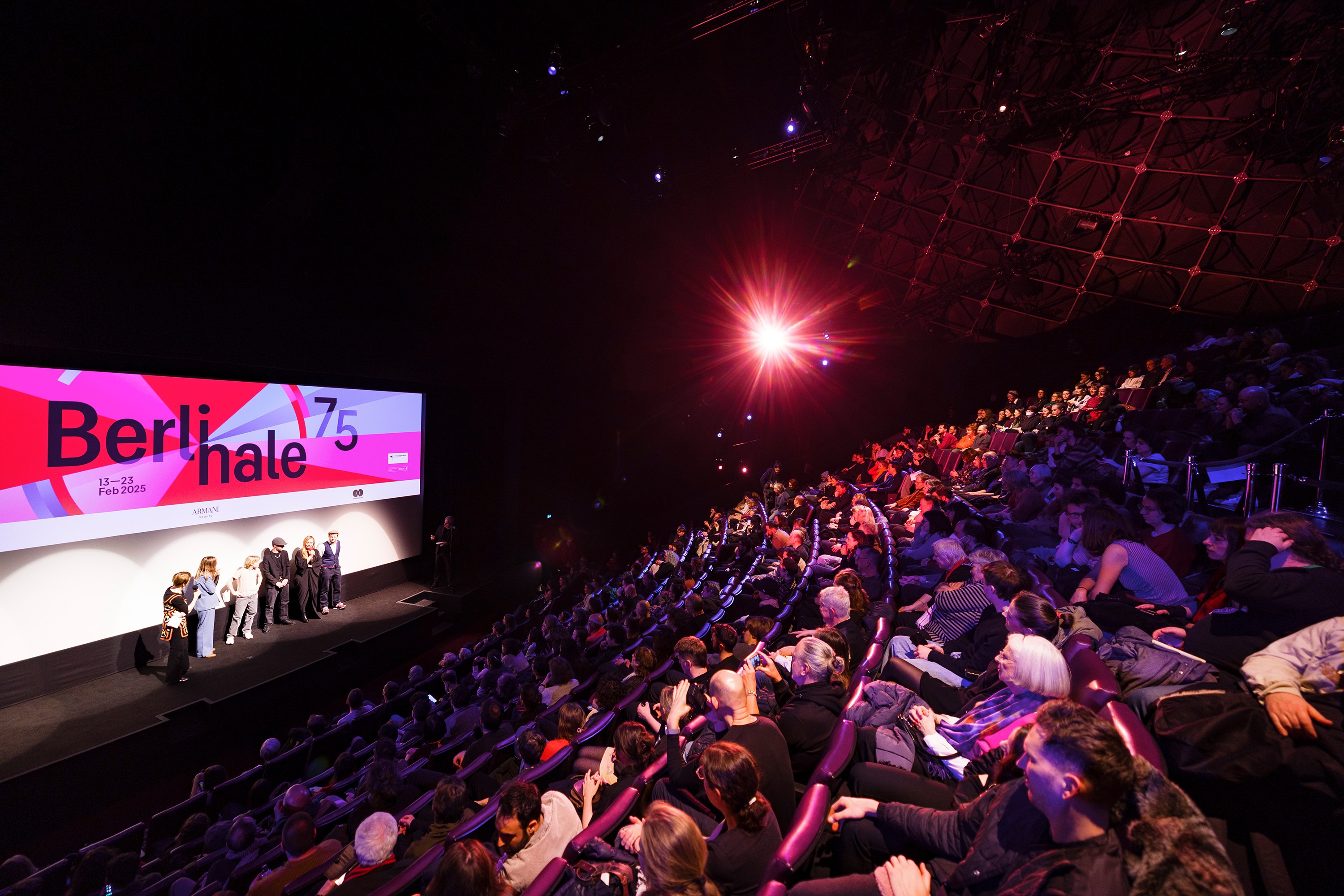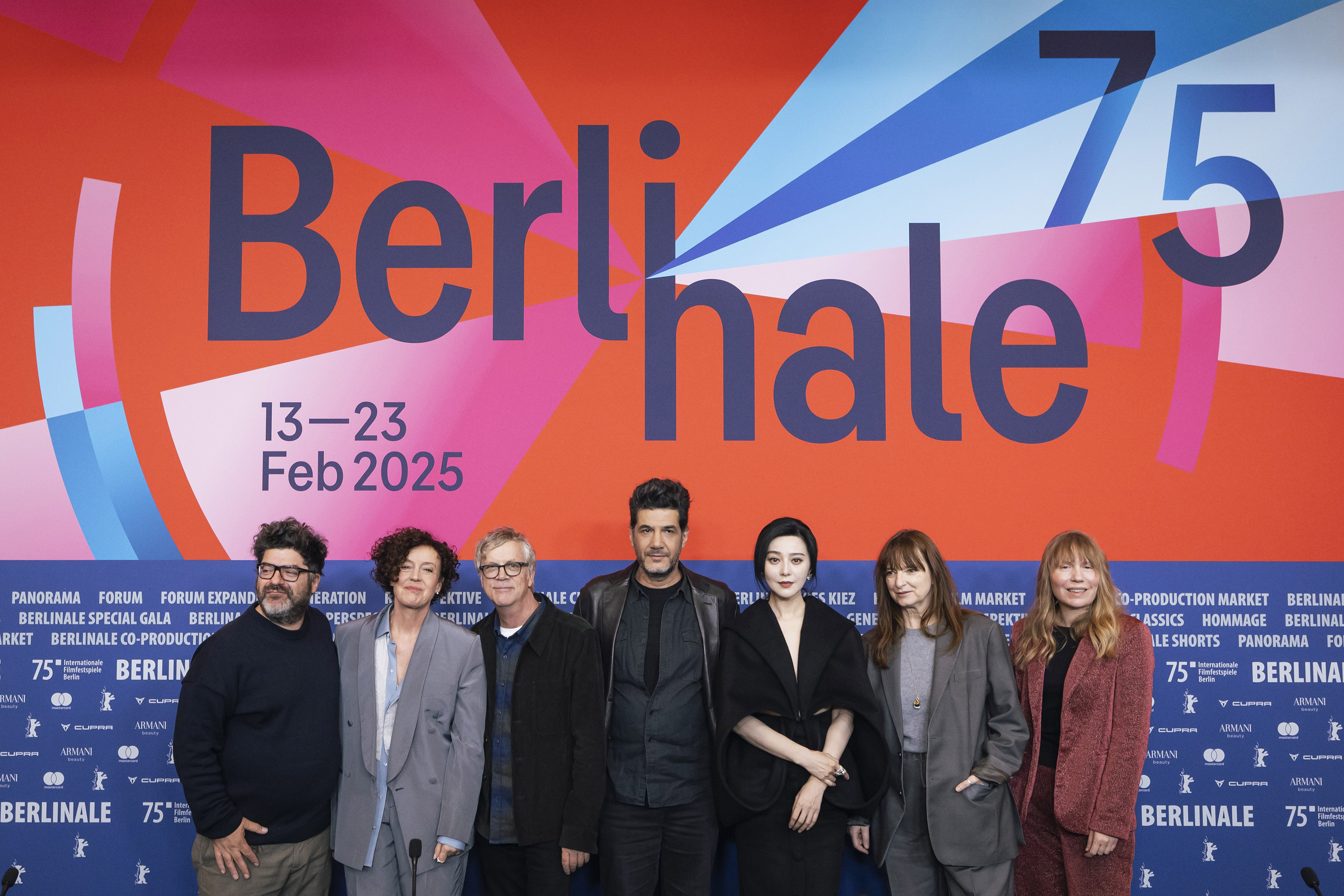
Das pulsierende Herz der Berlinale 2025
Fonts im Alltag: Pangea Condensed für die Berlinale 2025
Eine gut besuchte Premiere des Films „Minden Rendben“ im BlueMax-Theater am 14. Februar 2025 (© Dirk Michael Deckbar)
Mit der Berlinale 2025 feiern die Internationalen Filmfestspiele ihr 75-jähriges Jubiläum und gleichzeitig die erste Ausgabe unter der Leitung von Tricia Tuttle. Neben dem gedruckten Plakat stehen erstmals eine animierte Version des Posters und ein mp4-Keyvisual im Zentrum der Gestaltung. Damit unterstreichen die Veranstalter den Medienwandel hin zu digitalen Kanälen und die Bedeutung von Motion-Graphics in der Kommunikation.
Z
um fünften Mal liegt die Art Direction der Berlinale in den Händen von Claudia Schramke. Bereits während ihrer ersten Berufsausbildung von 2006 bis 2009 am Lette-Verein Berlin entdeckte sie ihre „Liebe zur Gestaltung, insbesondere zur Typografie". Den illustrativen, farbenfrohen Gestaltungsstil entwickelte sie danach an der Kunsthochschule Weißensee.
Das Keyvisual der Berlinale 2025 ist inspiriert von den fast vergessenen Film-Countdowns (engl: film leaders), die früher beim Einfädeln einer Filmrolle halfen. „Ich wollte etwas Lebendiges schaffen, das 75 Jahre Filmtradition feiert und des Themas ‚Zeit‘ eindrucksvoll interpretiert. Sozusagen das schlagende Herz der Berlinale.“ schreibt Claudia Schramke auf ihrer Website.
Zeitreise: Das animierte Keyvisual der 75. Berlinale ist inspiriert von den historischen Film-Countdowns.
Als Kontrast zu den kräftigen Farben suchte die Designerin eine hochwertige, klassisch anmutende Schrift. Sie stieß auf Pangea, entworfen von Christoph Koeberlin: „Weil sie von Christoph ist, muss sie gut sein.“ (Schramke).
Pangea Condensed ist wunderbar plakativ.
Besonders Pangea Condensed sei „wunderbar plakativ“. Überzeugt habe sie auch der umfassende Sprachausbau dieser Schrift, was für ein internationales Filmfestival von großer Bedeutung sei. „Das waren überzeugende Argumente für mich … rundum genial“, fasst sie ihre Entscheidung zusammen.
Wer mehr über Claudias Gedanken und Heransgehensweise erfahren möchte, sei auf das vom Goethe-Institut mit ihr geführte Interview verwiesen.
Pangea Condensed spielt die Hauptrolle auf dem Plakat und in den Keyvisuals der Berlinale 2025. (© Claudia Schramke)
Warten auf die S-Bahn (© Claudia Schramke)
Typischer Berliner Kiosk (© Claudia Schramke)
Souvenirs für Filmfans: Ein statisches Keyvisual ziert die Berlinale-Merchandise-Artikel 2025. (© Berlinale)
U-Bahnhof Friedrichstraße mit Souvenierjägern (© Claudia Schramke)
Programmheft (© Claudia Schramke)
Designerin Claudia Schramke neben ihrer Arbeit (© Claudia Schramke)
Die internationale Jury 2025: (v.l.n.r) Rodrigo Moreno, Maria Schrader, Todd Haynes, Nabil Ayouch, Fan Bingbing, Bina Daigeler und Amy Nicholson (© Dirk Michael Deckbar)
Plakatwand (© Claudia Schramke)
BlueMax-Theater (© Claudia Schramke)
Digitales Plakat am Potsdamer Platz (© Claudia Schramke)
Analoges Plakat am S-Bahnhof Alexanderplatz (© Claudia Schramke)
Neben dem Alexanderplatz (© Claudia Schramke)
Litfaßsäule am Zeiss-Großplanetarium (© Fontwerk)